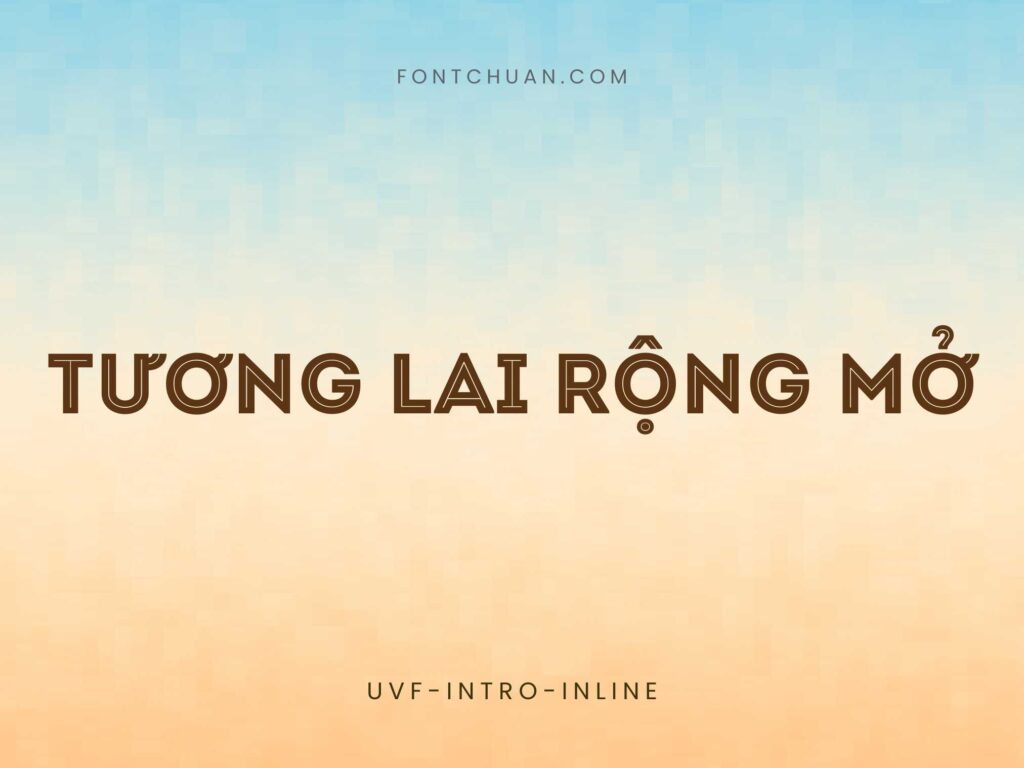
Font Intro Inline Việt Hóa
Font Intro Inline mang phong cách hiện đại với thiết kế dạng inline độc đáo, tạo điểm nhấn thị giác mạnh mẽ. Kiểu chữ này thuộc nhóm sans-serif với đường nét chắc chắn, độ tương phản thấp, giúp dễ đọc và linh hoạt trong thiết kế. Được ứng dụng rộng rãi trong lĩnh vực đồ họa, font này phù hợp cho các dự án sáng tạo cần sự chuyên nghiệp và nổi bật.
Với thiết kế tinh tế, Intro Inline đặc biệt thích hợp cho tiêu đề, quảng cáo, poster, bao bì sản phẩm và nhận diện thương hiệu. Nó cũng được sử dụng phổ biến trong ngành công nghệ, bất động sản, thiết kế nội thất và sáng tạo nội dung số. Nhờ vào phong cách mạnh mẽ, font này mang đến cảm giác hiện đại, sáng tạo và chuyên nghiệp trong mọi ứng dụng.